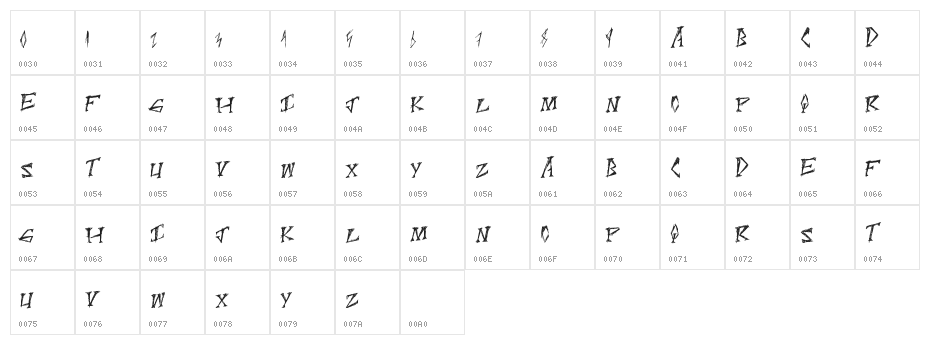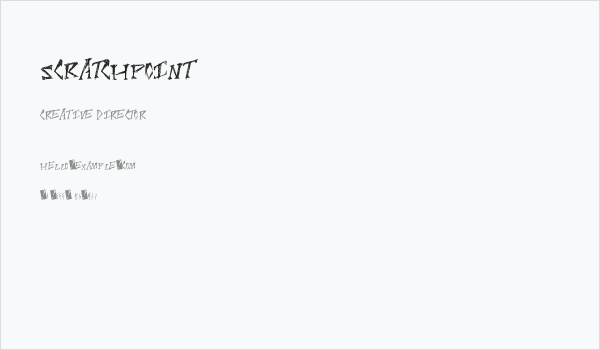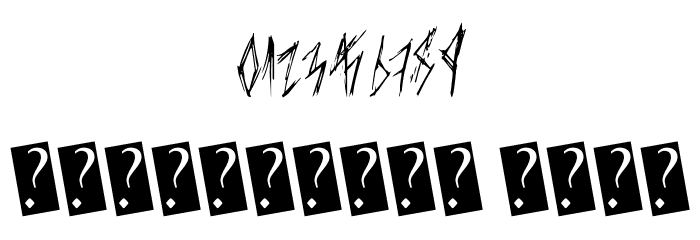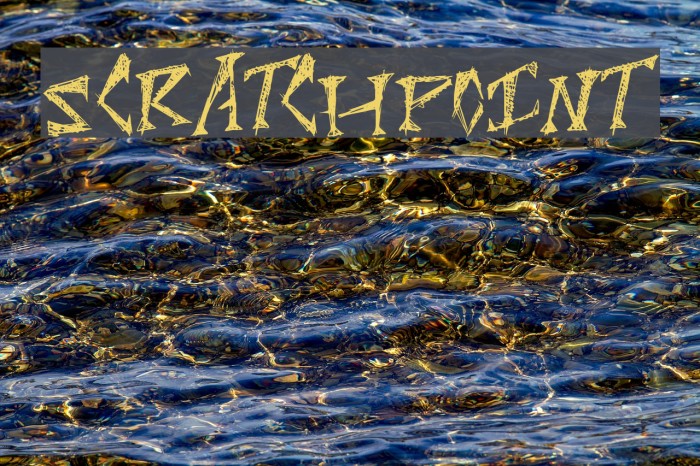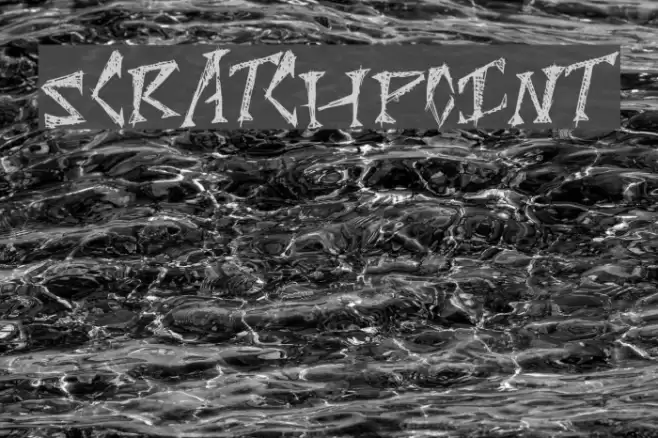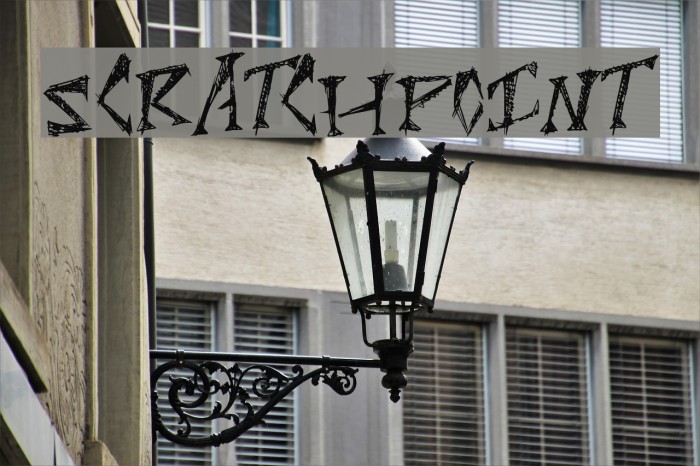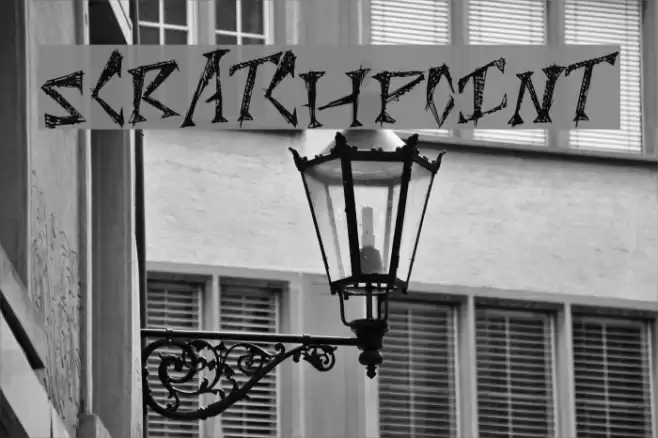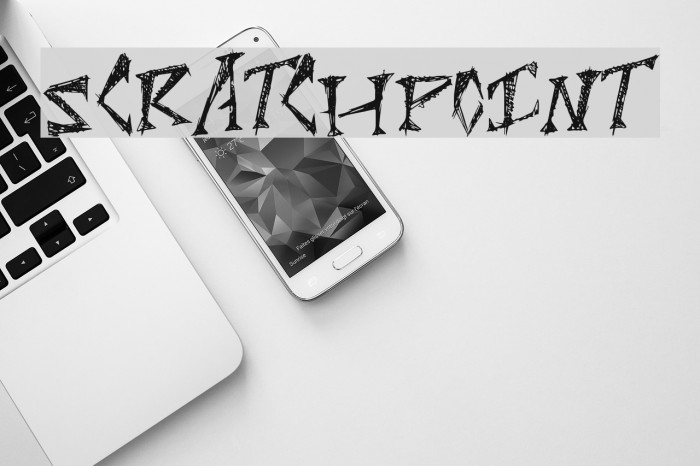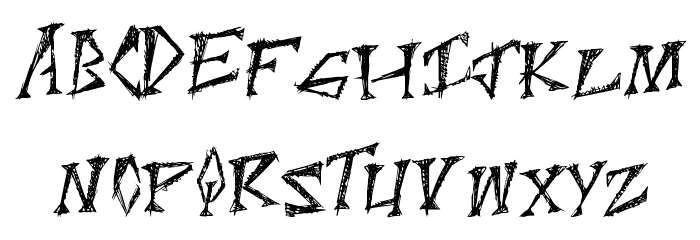
ScratchPoint Font
| Estilo general | Modern, Edgy |
| Caso de uso | Logos, Posters, Headlines |
| Proyectos propuestos | Ideal for music album covers, extreme sports branding, horror movie posters, and edgy fashion labels. |